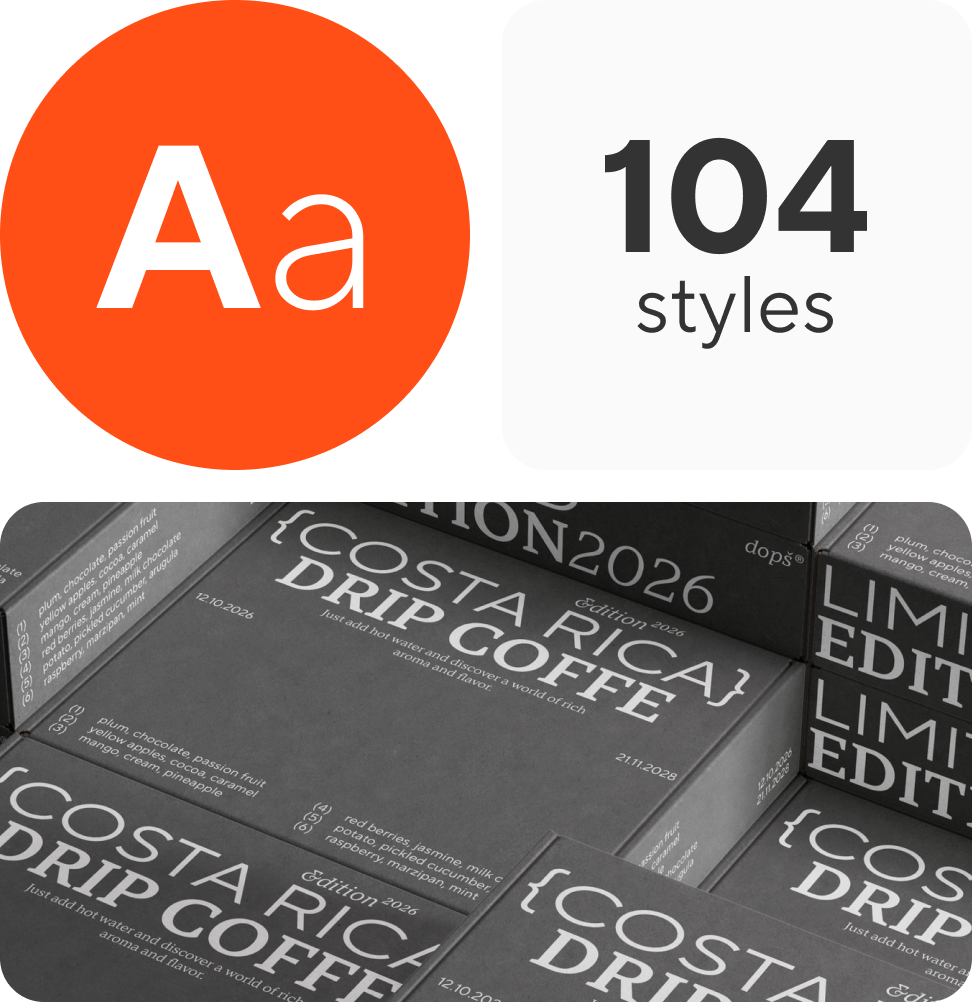
TT Bells сочетает в себе элегантную мягкость антиквы с непростым и дерзким характером, который выражается в прямых срезах и клинообразных засечках. В основе шрифта лежит ширококонечное перо, характерное для старостильных шрифтов, создающее эти атмосферные срезы и засечки.
TT Jenevers стилистически относится к голландским антиквам нового стиля. В гарнитуре присутствуют характерные детали, свойственные голландским антиквам — это ассиметричная форма засечек или нерегулярный наклон овалов.
TT Biersal — акцидентный гротеск со свободным, озорным и авантюрным характером. Отправной точкой для его создания послужил немецкий плакат начала 30-х годов. Мы хотели сохранить не только пропорции, но и ощущение небрежности, живости леттеринга из референса.
TT Globs — стильный брусковый шрифт с широкими пропорциями, живым дружелюбным характером и «летним» настроением.
TT Corals — это современный гуманистический гротеск, который имеет очень много характерных исторических черт начала 20-го века. Шрифт хорошо подойдет для темы классической литературы или музыки, а также для других самых разнообразных творческих областей человечества.